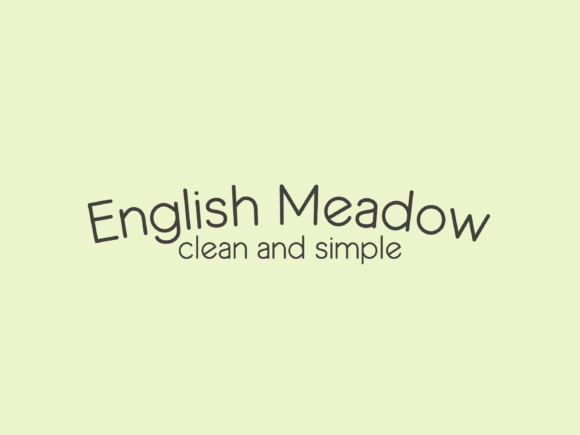
English Meadow
適切なデザイン要素を見つけるのは難しい場合がありますが、English Meadowは作品を即座に引き立てる優れたコレクションを提供します。
精密に作られたEnglish Meadowは、クリーンなベクター、滑らかなタイポグラフィ、そして安心のための商用ライセンスを提供します。